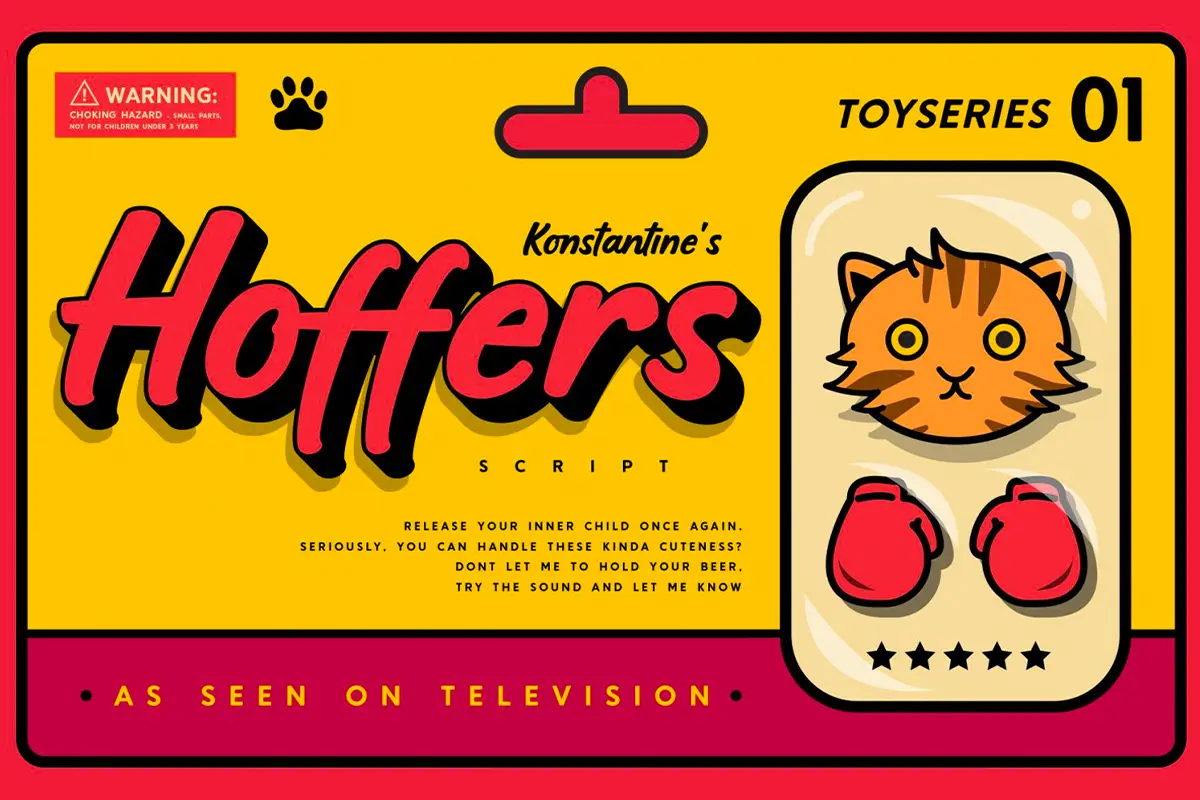
فونت دستنویس بولد
فونت Hoffers یک فونت دست نویس زیبا و جسورانه بولد یا ضخیم است که برای تیترها و پروژه‌های لوگوتایپ طراحی شده تا به آن‌ها جلوه‌ای شیک و خاص بدهد. این فونت با خوانایی قوی و شخصیت پویا، حس اعتماد به‌نفس و انرژی را منتقل می‌کند و می‌تواند به طراحی‌های شما حال‌وهوای نوستالژیک و منحصر‌به‌فرد ببخشد.
⭐ ویژگی‌های محصول
• فونت دست‌نویس با سبک جسورانه و شیک
• مناسب برای تیترها و لوگوتایپ‌ها
• انتقال حس قدرت، اعتماد به‌نفس و پویایی
• افزودن شخصیت نوستالژیک به طراحی‌ها
🎯 موارد استفاده
• طراحی لوگو و برندینگ
• ساخت تیترهای تبلیغاتی و پوسترها
• کارت‌های ویزیت و بسته‌بندی
• پروژه‌های خلاقانه با نیاز به جلوه خاص و نوستالژیک